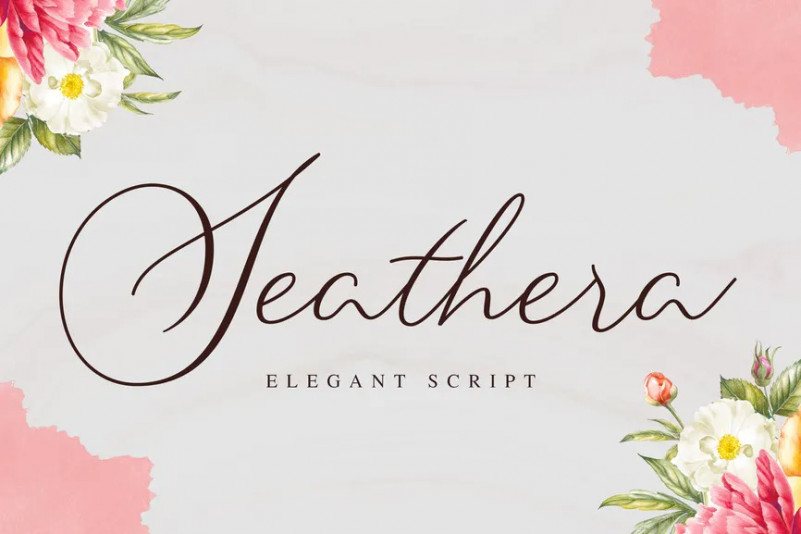
Seathera Font
Seathera est un beau script qui se sent chic, élégant et moderne. Il est parfaitement adapté à une grande variété de projets ! Cette police fait à la main rendra votre design a une belle touche naturelle pour chaque détail. Il est parfait pour tout projet de conception comme invitation, Logo, couverture de livre, artisanat ou tout autre motif de conception.